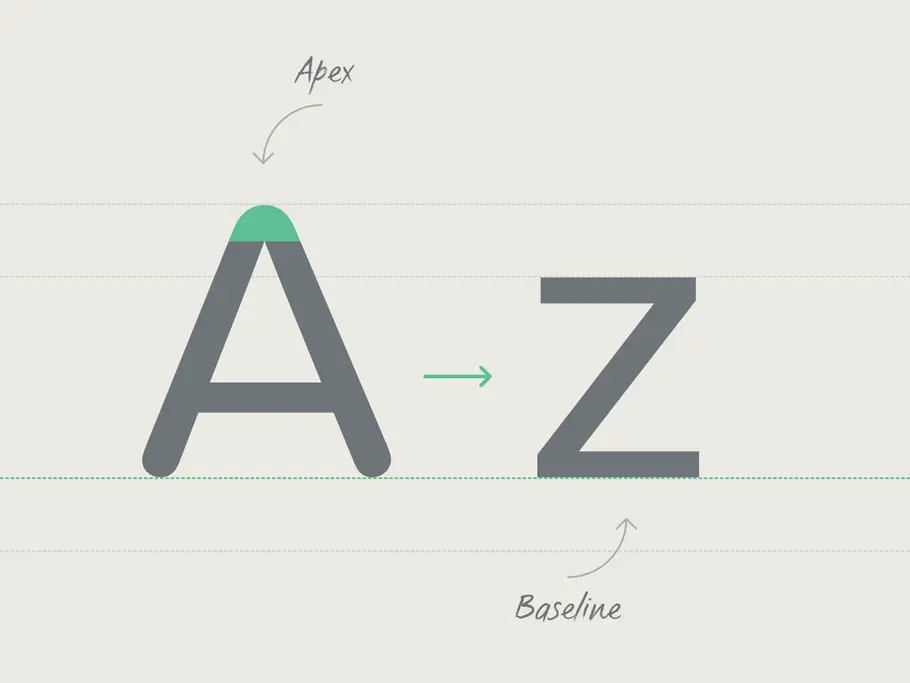
Das ABC der Buchstaben-Anatomie
Als Schriftgestalter isolieren wir uns mehr und mehr in einer abgeschlossenen typografische Blase. Wir vergessen dann, dass unsere Sprache, der Jargon, die Bezeichnungen und Fachbegriffe, die wir zum Diskutieren, zum Kritisieren und zum Verfeinern unserer Entwürfe verwenden, sich stetig erweitern oder neu definiert werden.
Irgendwann kam uns die Idee, die wichtigsten typografischen Fachausdrücke, die wir im Monotype Studio täglich verwenden, zu illustrieren und zu dokumentieren. Wir dachten so an zwei Dutzend Termini, doch ehe, die wir uns versahen, waren wir bei fast 80 Begriffen angelangt. Da wir die Liste nicht kürzen wollten, haben wir diese Infografik erstellt, die das gesamte Typo-Vokabular an einem Ort auflistet. Gleichzeitig haben wir unsere Lieblingsschrift FS Aldrin für die Titel und die Beschreibungen getestet. Ihre technischen und präzisen Formen schienen perfekt geeignet, um alle Begriffe in einem knappen, aber auch sympathischen Tonfall zu vermitteln.
Anti-aliasing
Halbtransparente Pixel entlang der Buchstabenkonturen, die stufige Kurven und Diagonalen weichzeichnen
Antiqua / Antikva
Schriftgattung. Ab 1470 für den Buchdruck verwendeten rundbogige Lettern römischen Ursprungs (mit Serifen)
Aperture
Öffnung
Die (variierbare) Öffnung eines nicht geschlossenen Binnenraums (Punze)
Apex
Scheitel
Wendepunkt, an dem Aufstrich und Abstrich zusammenlaufen.
Arc
Abstrich
(Meist gebogene) Endung eines Buchstabens
Arm
Horizontale Linie bei Großbuchstaben, die an einem oder beiden Enden nicht mit einem anderen Strich verbunden ist
Ascender
Oberlänge
Oberer Teil (ab Mittellänge) eines Kleinbuchstabens
Ascender line
Oberlänge, k-Linie
Unsichtbare Linie, die die Höhe aller Oberlängen in einer Schrift markiert
Axis / Stress
Neigungsachse
Unsichtbare Linie, die die Glyphe an ihrer dünnsten Stelle von oben nach unten durchschneidet
Ball terminal
Tropfen(serife)
Runder Buchstabenabschluss einer Serifenschrift
Baseline
Grundlinie
Unsichtbare Linie, auf der die Buchstaben einer Schrift stehen
Beak
Schnabel
Zierstrich am Ende des Arms eines Buchstabens, ähnlich einer Serife, aber prägnanter
Bilateral serif
Doppelseitige Serife
Serife, die sich zu beiden Seiten eines Strichs erstrecken (vgl. Halbserife)
Bowl
Bauch
Geschlossene Rundung innerhalb der Mittellänge bei d, b, p und q
Bracket
Kehlung
Gebogene oder gewinkelte Verbindung zwischen Schaft und Serife
Cap height
Versalhöhe
Höhe der Großbuchstaben, gemessen von der Grundlinie
Condensed
Schriftvariante mit schmalen Zeichenproportionen
Counter
Punze, Innenraum
Ganz („Auge“) oder teilweise von einer Buchstabenform umschlossene, nicht druckende Innenfläche, z. B. bei p, o, c
Cross stroke
Querstrich
Der horizontale Strich über ein kleines t oder f
Crossbar
Querbalken
Horizontaler Strich wie die Mitte eines H, A oder e
Crotch
Schritt
Spitzer, nach innen gerichteter Winkel an der Verbindung zweier Striche, zum Beispiel bei N, V, w und y.
Cursive
Kursive
Handschrift mit verbundenen Buchstaben und Bezeichnung für eine in Schreibrichtung geneigte Auszeichnungsschrift.
Descender
Unterlänge
Unterer Teil von Kleinbuchstaben, der unter die Grundlinie reicht
Descender line
Unterlänge, p-Linie
Unsichtbare Linie, die den untersten Teil der Unterlängen markiert
Display font
Displayschrift
Fantasievoll konstruierte Schriften für Werbung, Verpackungsdesign und Shop-Schilder
Ear
Ohr, Fähnchen
Häkchen am geschlossenen Kleinbuchstaben g
Eye
Auge
Anderer Name für einen geschlossenen Innenraum (Punze)
Finial
Auslauf
Verjüngtes oder geschwungenes Bogenende, z. B. bei c und e, oder der obere Abstrich eines doppelstöckigen a
Flag
Fahne
Waagerechter Strich am Kopf der Ziffer 5
Foot
Sockel
Der untere Teil eines Stamms, der auf der Grundlinie ruht
Gadzook
Klammer
Ein Verbindungsbogen in einer Ligatur, die ursprünglich nicht zu einem der Buchstaben gehört
Glyph
Glyphe
Ein einzelnes Zeichen (Zahl, Buchstabe, Satzzeichen oder Symbol) wird durch seine Glyphe repräsentiert
Grotesk
Ältere deutsche Bezeichnung für Sans Serif
Hairline
1. Bezeichnung für den leichtesten Schnitt einer Schriftfamilie; 2. für den dünnsten Strich eines Buchstabens
Halbfett
Bezeichnung einer Strichstärke zwischen Medium und Fett
Head serif
Kopfserife
Halbserife am oberen Anfangspunkt der Buchstabenform
Hinting
Anweisungen in einer digitalen Schriftdatei für die störungsfreie Wiedergabe auf niedrig auflösenden Ausgabegeräten
Hook
Rücken
Geschwungener Bogen in Kleinbuchstaben, z. B. f, h und n
Ink trap
„Lichtkeil“ oder „Einstich“ im spitzen Winkel von Buchstaben, um das Zufließen mit Druckfarbe zu vermeiden
Italic
Italic, Kursive
Auszeichnungsschrift: Nach rechts geneigte Version einer Roman mit Handschriftmerkmalen
Joint / Juncture
Knoten
Zusammenlauf mehrerer Striche
Kerning
Unterschneidung, Kerning
Optischer Ausgleich des Abstands von Buchstaben, um „Löcher“ im Schriftbild zu vermeiden.
Leading / Linespacing
Zeilenabstand
Vertikaler Abstand zwischen den Textzeilen, von Grundlinie zu Grundlinie
Leg
Bein
Abwärts gerichteter Strich bei k und R
Ligature
Ligatur
Zwei oder mehr Buchstaben, die zu einer Glyphe zusammengefügt sind, z. B. fi oder ffj
Link / Neck
Steg
Verbindende Linie, die den oberen und unteren Teil eines dreistöckigen g zusammenhält
Loop / Lobe
Bogen
Eine abgerundete, geschlossene oder teilweise geschlossene, ausladende Kurve
Midline
Mittellänge, x-Höhe
Unsichtbare Linie, die auf dem oberen Ende der Kleinbuchstaben ruht
Oblique / Slanted
Maschinell verschrägter Schriftschnitt, der im Gegensatz zur echten Kursiven nicht entworfen und optisch korrigiert wird
Old style / Hanging figures
Mediävalziffern
Ziffern mit Groß- und Kleinbuchstaben-Proportionen, die im Fließtext den Lesefluss weniger stören als Versalziffern
Overshoot
Überhang
Teile von runden und spitzen Lettern, die über die Schriftlinien hinausragen zwecks optischer Größengleichheit
Pica
Eine typografische Maßeinheit, die 12 Punkten oder Pixeln entspricht
Point
Punkt
Eine typografische Maßeinheit, die 1/12 eines Pica oder 1 Pixel entspricht
Point size
Punktgröße
Die (relative) Größe des Körpers eines jeden Zeichens in einer Schriftart
Pro
Namenszusatz für Fonts, die einen erweiterten Sprachausbau aufweisen, z. B. mit kyrillischem und griechischem Zeichensatz
Rasterization
Rastern
Umwandlung eines vektorbasierten Schriftbildes für die Ausgabe in Pixel, im Druck oder am Bildschirm
Roman
Standard- oder der Regular-Schnitt einer aufrechten Schrift
Serif
Kurze dünne Linie, die bei Antiqua-Schriften einen Buchstabenstrich am Ende, quer zur Grundrichtung abschließt
Shoulder
Schulter
Obere Rundung bei Kleinbuchstaben wie m, n, a und h
Single-tier
einstöckig
Wenn ein a geschlossen ist und ein g offen; Gegenteil: doppelstöckig
Small caps
Kapitälchen
Auszeichnungsschrift: Großbuchstaben in der Höhe von Kleinbuchstaben, aber mit gleicher Strichstärke (nicht skaliert)
Spacing
Zeichenabstand
Der vom Schriftentwerfer definierte Abstand der Buchstaben einer Schrift
Spine
Rückgrat
Die Kehre im großen S sowie in der 8
Spur
Sporn
Kleine Ecke, die im Zusammenspiel mit Serifen oder Strichen eine Art optisches Gegengewicht erzeugt
Spurless
spornlos
Kurven gehen ohne Ableger in gerade Stämme über
Stem
Stamm
Senkrechte und zugleich stärkste Linie innerhalb eines Buchstabens
Swash
Übertriebene dekorative An- und Abstriche; Schwungbuchstaben
Tail
Schweif, Cauda
Abstrich am Q; Cauda = lateinischer Begriff für „Schwanz“
Taper
Auslauf
Dünneres und feineres Ende eines Abstrichs
Terminal
Endstrich
Das Ende eines jeden Strichs, der keine Serifen hat
Tittle
i-Punkt
Zu finden auf den Buchstaben i und j, kann rund, quadratisch oder eine andere Form haben
Tracking
Spationierung, Sperrung
Zu Buchstabengruppen hinzugefügter oder entfernter Abstand außerhalb des definierten Zeichenabstands
Vertex
Spitze
Der Punkt, an dem sich zwei Striche am unteren Rand eines Zeichens treffen
Weight
Strichstärke
Die Fette einer Schrift, unabhängig von ihrer Größe; kann sich auf einen Stil innerhalb einer Familie beziehen: Regular, Bold, …
X-height
x-Höhe, Mittellänge
Höhe des Kleinbuchstabens x; Richtwert für die Höhe der Kleinbuchstaben und damit für die optische Schriftgröße